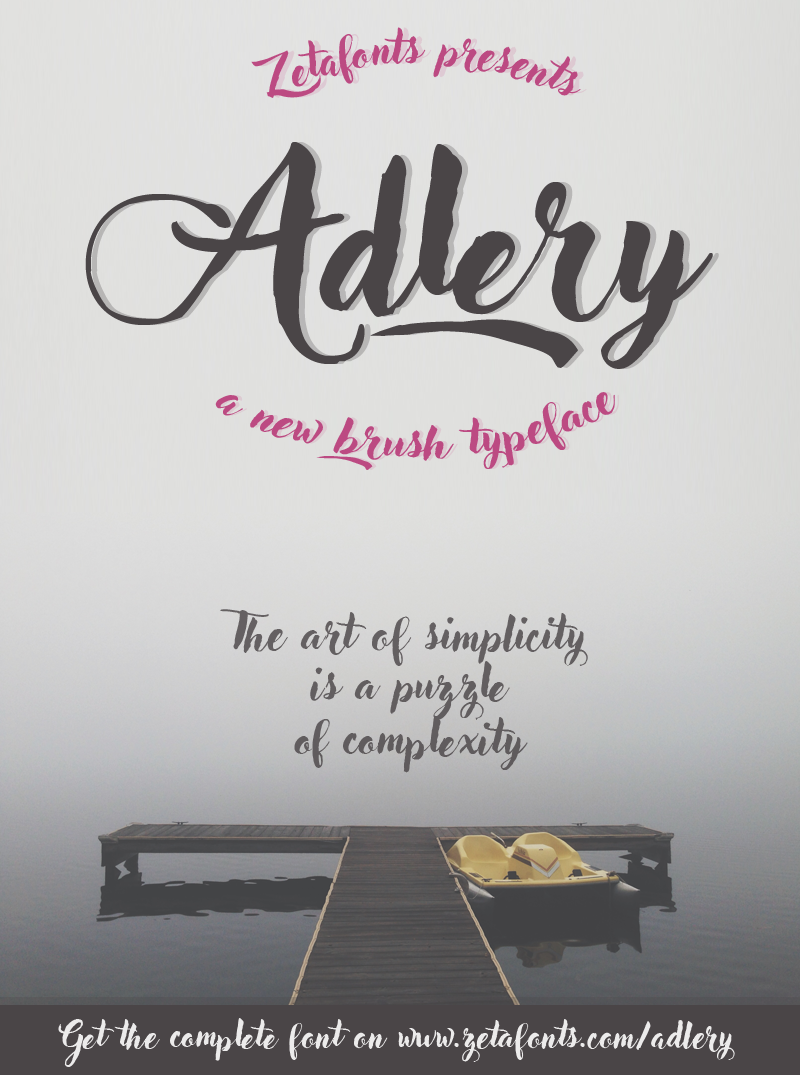
Adlery Brush Font – Fonte Grátis
Adlery Brush Font
A fonte Adlery Brush é uma opção ideal para quem deseja adicionar um toque artesanal a seus projetos digitais. Desenhada por Zetafonts, ela se destaca pela sua aparência de escrita à mão e foi otimizada para garantir uma leitura clara em grandes tamanhos médios. O que torna esta fonte única é o seu conjunto duplo de letras minúsculas alternando entre a escrita, evitando assim que os mesmos caracteres se repitam. Para quem busca algo além da tipografia tradicional e está procurando por uma fonte com um toque criativo e autêntico, Adlery Brush é a escolha perfeita para criar um design único e sofisticado em páginas de download e projetos gráficos.